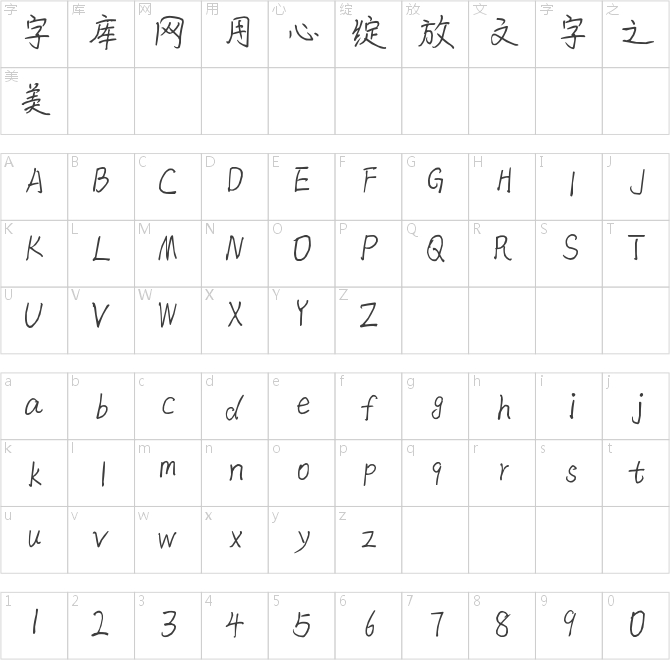
字體名稱: 伯樂槐樹體
伯樂槐樹體
伯樂槐樹體介紹
伯樂槐樹體字體下載BoLeHuaiShuti
伯樂槐樹體字體BoLeHuaiShuti字庫是一款讓人賞心悅目、百看不厭的中文字體,適合各類廣告和產品包裝設計應用,字體大小3.36MB,格式為ttf字體,上傳用戶是17199970014,作者/版權方為伯樂字庫